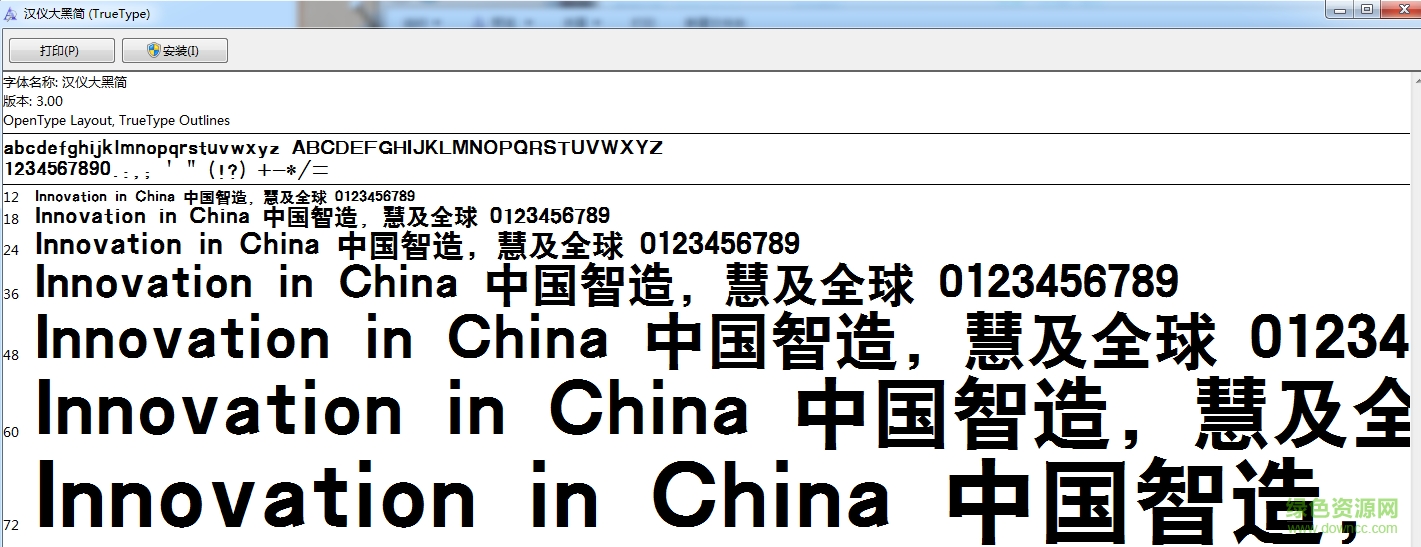
漢儀大黑簡(jiǎn)體字體是一款很有厚重莊嚴(yán)感的漢儀字體,使用于正規(guī)場(chǎng)合的設(shè)計(jì)排版需要,本字體支持所有windows系統(tǒng)和蘋(píng)果MAC系統(tǒng),歡迎大家下載體驗(yàn)!
漢儀大黑簡(jiǎn)字體樸素大方、結(jié)構(gòu)嚴(yán)謹(jǐn),非常引人注目,常用作印刷中穩(wěn)重、醒目的標(biāo)題字。